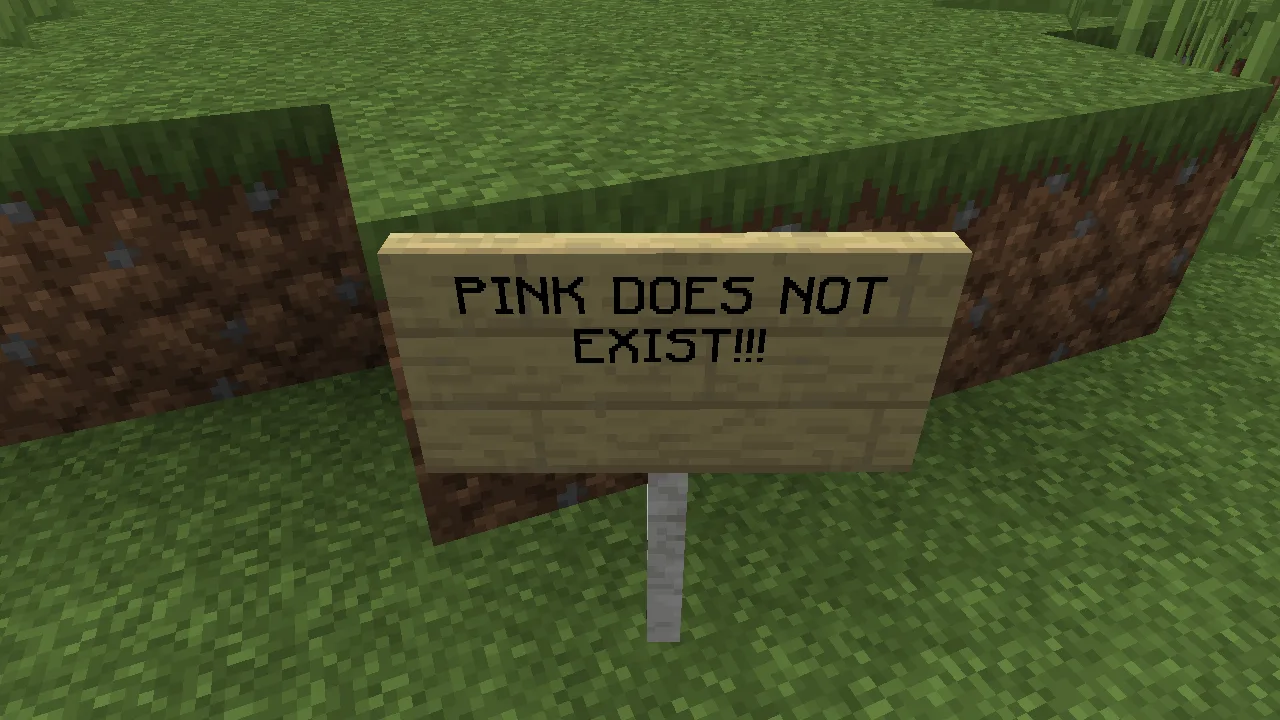
Ресурспак Better Fonts улучшает читаемость текста в Minecraft, используя 32x разрешение и стилистически согласованный шрифт.
Что дает этот resource pack
Этот ресурспак представляет собой небольшую модификацию стандартного Minecraft с разрешением 32x, что способствует лучшей читаемости текста в игре. Он обеспечивает более чёткое и стилистически единообразное отображение шрифтов, уменьшая трудности при чтении.
Ресурспак выполнен в ванильной тематике, предоставляя улучшенную визуальную ясность без изменения общего стиля игры. Он совместим с указанными версиями Minecraft и направлен на повышение удобства использования интерфейса.